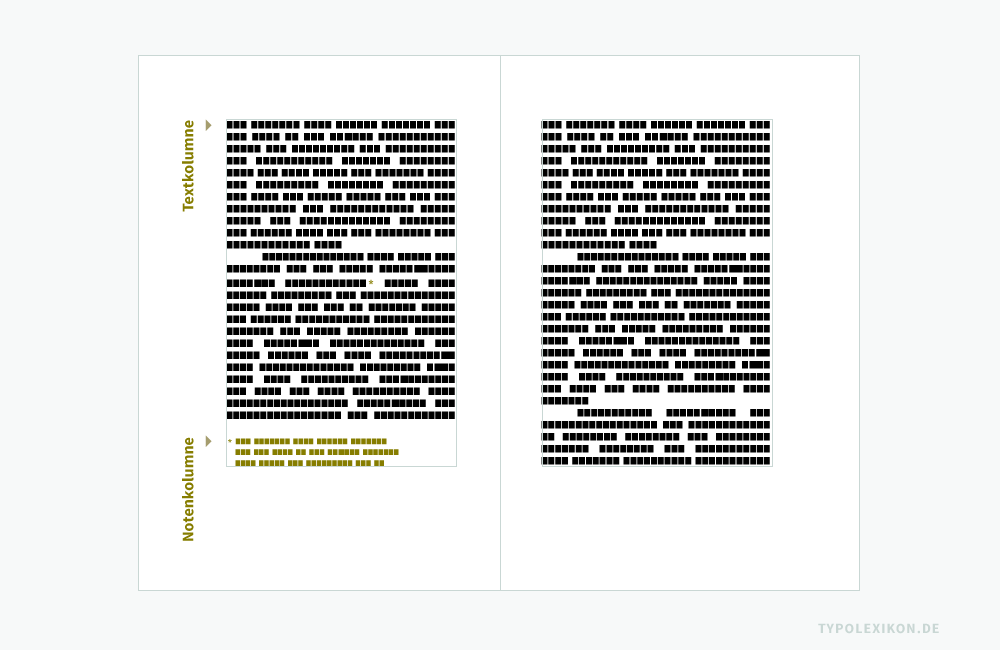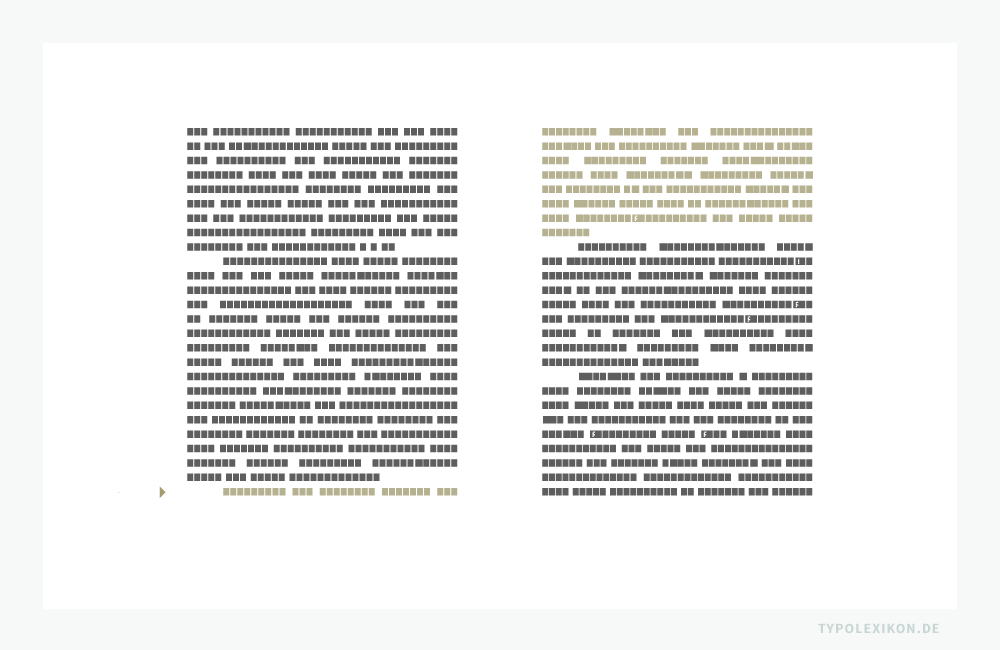
Umbruch
In der Typografie versteht man unter »Umbruch« das Umbrechen von Textzeilen, Kolumnen (Satzspalten) und Seiten unter Berücksichtigung orthografischer, typografischer, ästhetischer und themenbezogenen Regeln und Betrachtungsweisen, beispielsweise um ein Buch, eine Zeitung, ein Prospekt oder eine Website sinngemäß und ästhetisch zu gliedern; Text, der am Zeilenende umbrochen und in einer neuen Zeile auf der gleichen oder einer nachfolgenden Seite fortgeführt wird; Austarieren aller Zeilenumbrüche eines geschlossenen Schriftsatzes. Textumbruch; Verb »umbrechen«. Alternative Bezeichnung »Mettage«.
Unter »Umbruch« wird das Umbrechen von Headlines, Sublines, Fließtext, Textzeilen, Satzspalten und Seiten unter Berücksichtigung orthografischer, typografischer, ästhetischer und themenbezogenen Regeln und Betrachtungsweisen verstanden, beispielsweise um eine Tageszeitung sinngemäß und ästhetisch zu gliedern. Bildzitat: Süddeutsche Zeitung, München.
Da bereits der Bruchteil eines Millimeters oder Gevierts (z.B. in einer Satzbreite) das Umbrechen einer Zeile und das Umbruchverhalten einer Schrift (z.B. in der Normalschriftweite) verändern können, zählt der Umbruch zur Mikrotypografie.
Der typografische Umbruch umfasst:
• Zeilenumbruch
• Kolumnenumbruch
• Seitenumbruch
Ursprung des Begriffs »Umbruch«
In der Periode des materiellen Schriftsatzes mit physischen Drucktypen aus Metall (z.B. aus einer Blei-Zinn-Antimon-Kupfer-Legierung) arbeiteten in der Regel mehrere Handschriftsetzer an einem »Werk« (Buch) bzw. an einer Zeitung, selten eine Person alleine.
Um mehrere Handsetzer zu koordinieren und den komplexen Workflow zu organisieren, entstand mit der Industrialisierung und der einhergehenden Prosperität der Typografie im frühen 19. Jahrhundert das eigenständige Berufsbild des »Metteur en pages«, kurz »Metteur« genannt, was bis in die 1970er Jahre im gewerbespezifischen Sprachschatz deutschsprachiger Schriftsetzer auch mit »Fertigmacher«, »Seitenformer«, »Seitengestalter«, »Umbruchgestalter«, »Zurichter« oder als »Umbrecher« übersetzt wurde.
Die Tätigkeit eines Metteurs – des Umbrechers – bezeichnete man als »Umbruch«, »Umbrechen«, »Zurichten« oder als »Mettage«.
Formgerechter Umbruch
Im Laufe der Jahrhunderte haben sich Erfahrungswerte, Regeln und typografische Betrachtungsweisen etabliert, die beschreiben, wie ein Umbruch zu sein oder nicht zu sein hat. Grundsätzlich gilt in der angewandten Typografie das Ideal: Ein formgerechter oder gar ästhetischer Umbruch optimiert spürbar den Grauwert, die Lesemotivation und die Lesbarkeit eines schriftbasierten Mediums. Im besten Falle berücksichtigt ein Umbruch nicht nur typografische und orthografische Regeln, sondern auch den Leseprozess (siehe u.a. Fixationen), semantische sowie linguistische Aspekte.
Umbruchfehler
Neben sprachspezifischen orthografischen Regeln für einen Zeilenumbruch durch Silbentrennungen, existiert in der angewandten Typografie bzw. im professionellen Schriftsatz darüber hinaus eine Vielzahl von Regeln und Lehrsätzen, wie ein korrekter Zeilen-, Kolumnen- und Seitenumbruch auszusehen hat. Die Fehler im Zeilen-, Kolumnen- und Seitenumbruch werden als »Umbruchfehler« bezeichnet.
Insbesondere ein Umbruch mit vielen Headlines, Initialen, Ausgangszeilen und Konsultationen (z.B. Fußnoten) gilt als sehr aufwendig und ist dementsprechend sehr fehleranfällig.
Zu den wichtigsten typografischen Regeln für einen fehlerfreien Umbruch zählen (alphabetisch geordnet): 1)
Abkürzungen
• Abkürzungen (z.B. e. V., UStG oder GmbH) werden nicht umbrochen
• Lexikalische Abkürzungsweisen am Ende einer Zeile (z.B. sphd.) gelten als unschön
Absatzende
• Der Zeilenausgang in der letzten Zeile eines Absatzes muss den nachfolgenden Einzug »decken« bzw. nicht kürzer sein, als der Leerraum vor dem Einzug ist
• Der Zeilenausgang in der letzte Zeile eines Absatzes sollte kürzer als die maximale Satzbreite sein
• Kein neuer Absatz durch Texteinzug in der letzten Zeile einer Seite bzw. Kolumne
Auszeichnungen
Datum und Uhrzeit
• Ein Datum in Form von Ziffern und Gliederungszeichen (z.B. 17.3.2019) darf nicht umbrochen werden
• Ein Datum in Form von Ziffern, Gliederungszeichen und ausgeschriebenen Monat (z.B. 15. Dezember) darf nicht umbrochen werden. Formschön ist, wenn Tag, Monat und Jahr (z.B. 15. Dezember 2019) in der gleichen Zeile stehen. Eine Silbentrennung im Monat gilt als akzeptabel
• Eine Uhrzeit in Form von Ziffern und Gliederungszeichen (z.B. 13:40) darf nicht umbrochen werden. Formschön ist, wenn die Uhrzeit und das Wort »Uhr« (z.B. 13:40 Uhr) in der gleichen Zeile stehen
Horizontalstriche
• Ein Bindestrich bei Zusammensetzungen mit Buchstaben (z.B. E-Mail) und Arabischen Ziffern (z.B. 100-jährig) sowie in Kombination (z.B. 20-Euro-Gutschein) wird nicht umbrochen
• Ein  »Bis-Strich« (z.B. 17:30–18:00 Uhr) wird nicht umbrochen
• Einen Bindestrich zwischen Substantiven (z.B. Renaissance-Antiqua) oder Adjektiven (z.B. russisch-orthodox) 2)  zu umbrechen, gilt als unschön. Falls dies nicht vermeidbar ist, erfolgt der Umbruch nach dem Divis
↑8 Anmerkung: In HTML-Texten ist es zwar möglich, Formatierungsanweisungen per CSS zu erteilen (z.B. geschützte Leerzeichen), diese müssen aber sehr aufwendig eingepflegt werden. Bei längeren Texten oder in CMS-Anwendungen ist dies in der Praxis zu aufwendig oder für einen normalen User schlicht und einfach nicht möglich.